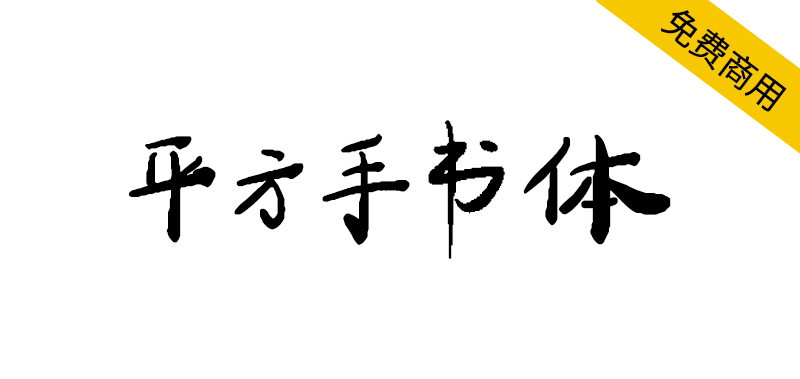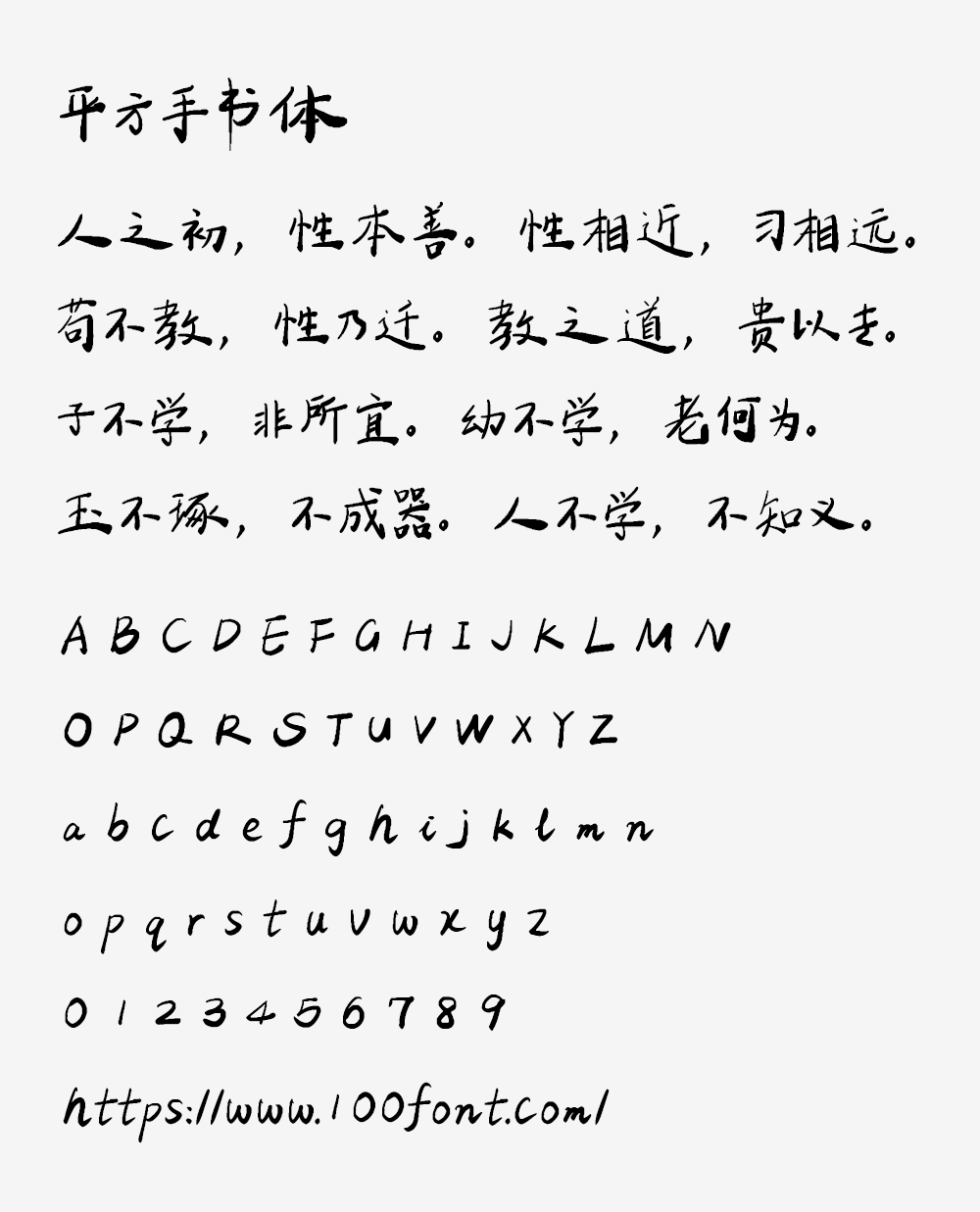
【平方手书体】一款优雅的艺术手写体字体
寻找一款既优雅又实用的艺术手写体?平方手书体以其粗细适中的笔画和自然流畅的书写风格,为设计注入独特视觉美感。从艺术创作到商业广告,从书法练习到自媒体排版,它都能完美胜任。令人惊喜的是,这款高品质字体允许个人和企业免费商用,为创意工作提供无限可能,只需遵守基本使用规范。
【平方手书体】一款优雅的艺术手写体字体
平方手书体是一款艺术手写体字体,其笔画粗细适中,书写自然流畅,呈现出优雅的视觉美感,适用于艺术创作、平面广告设计、书法临摹练习等设计需求。
【平方手书体】一款优雅的艺术手写体字体